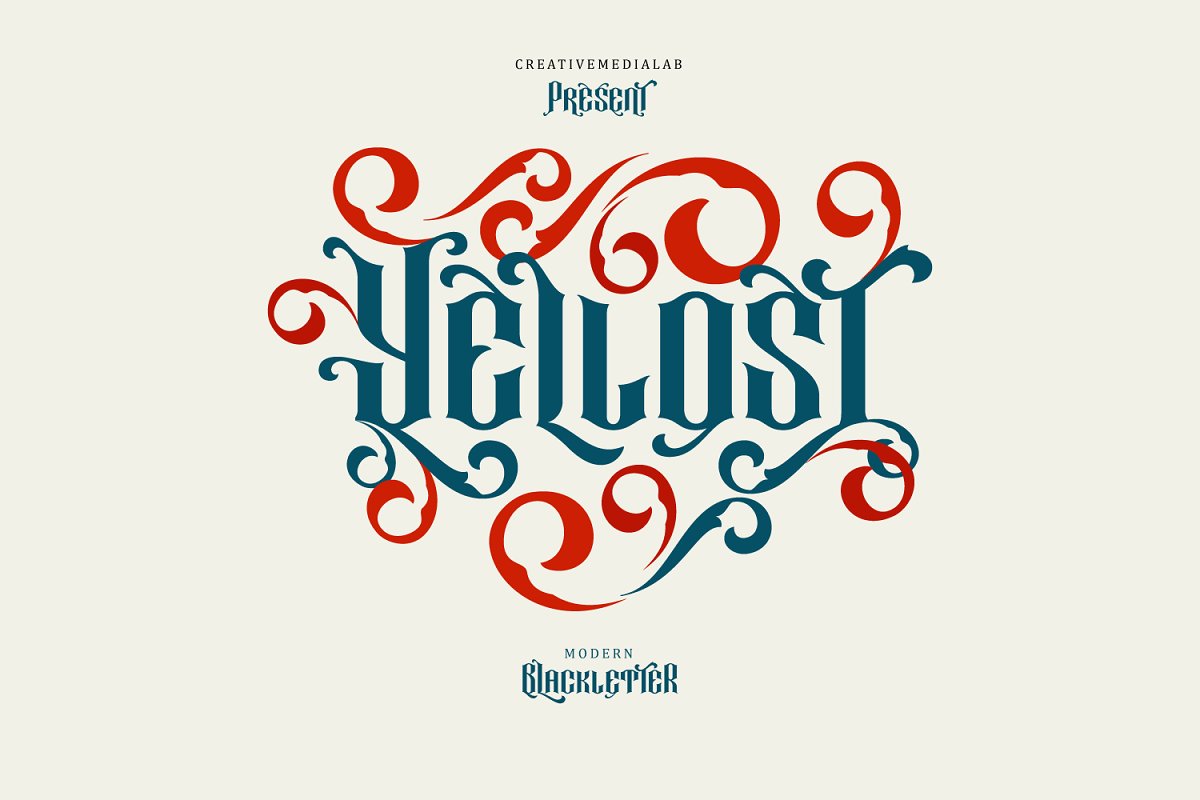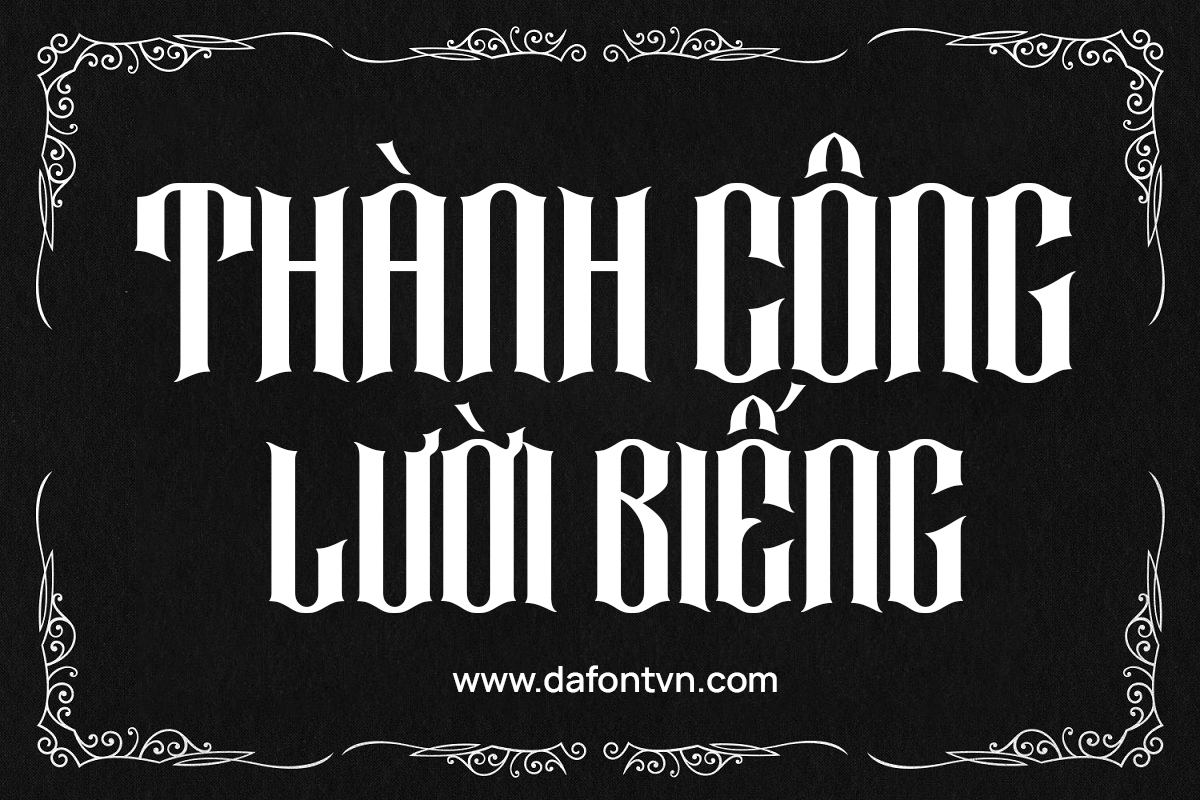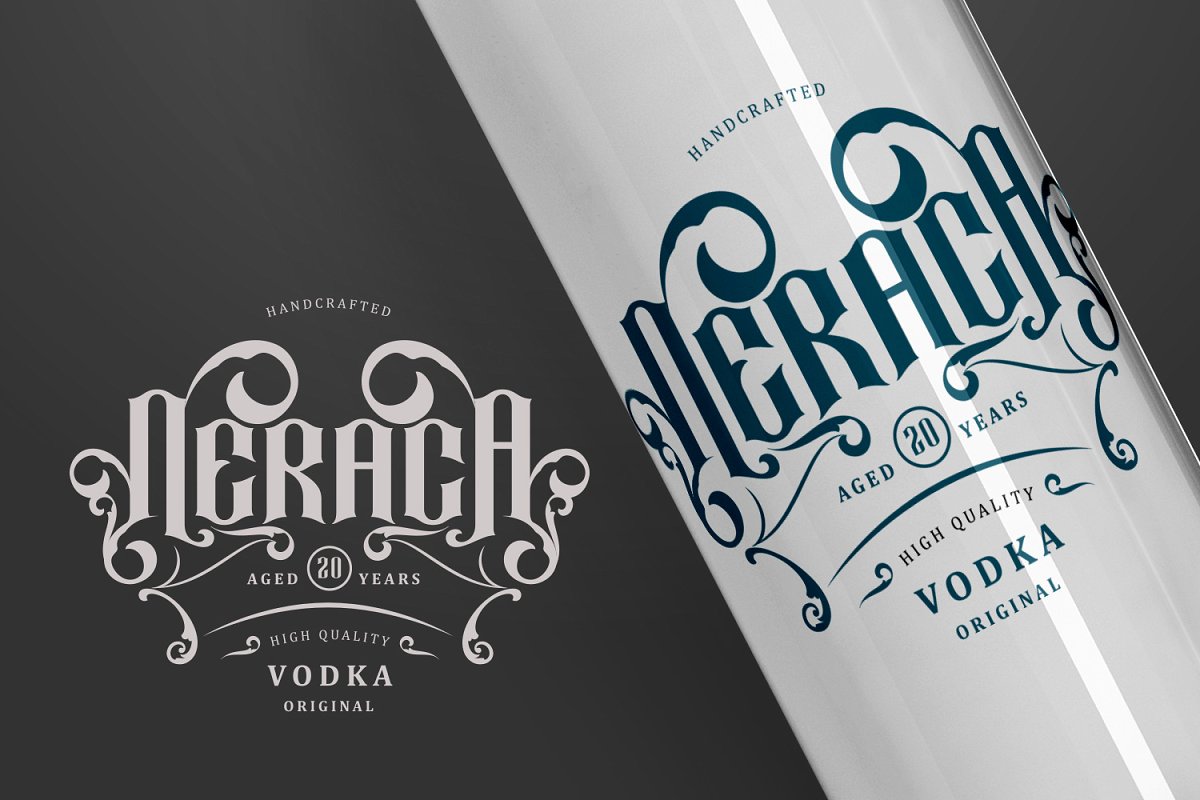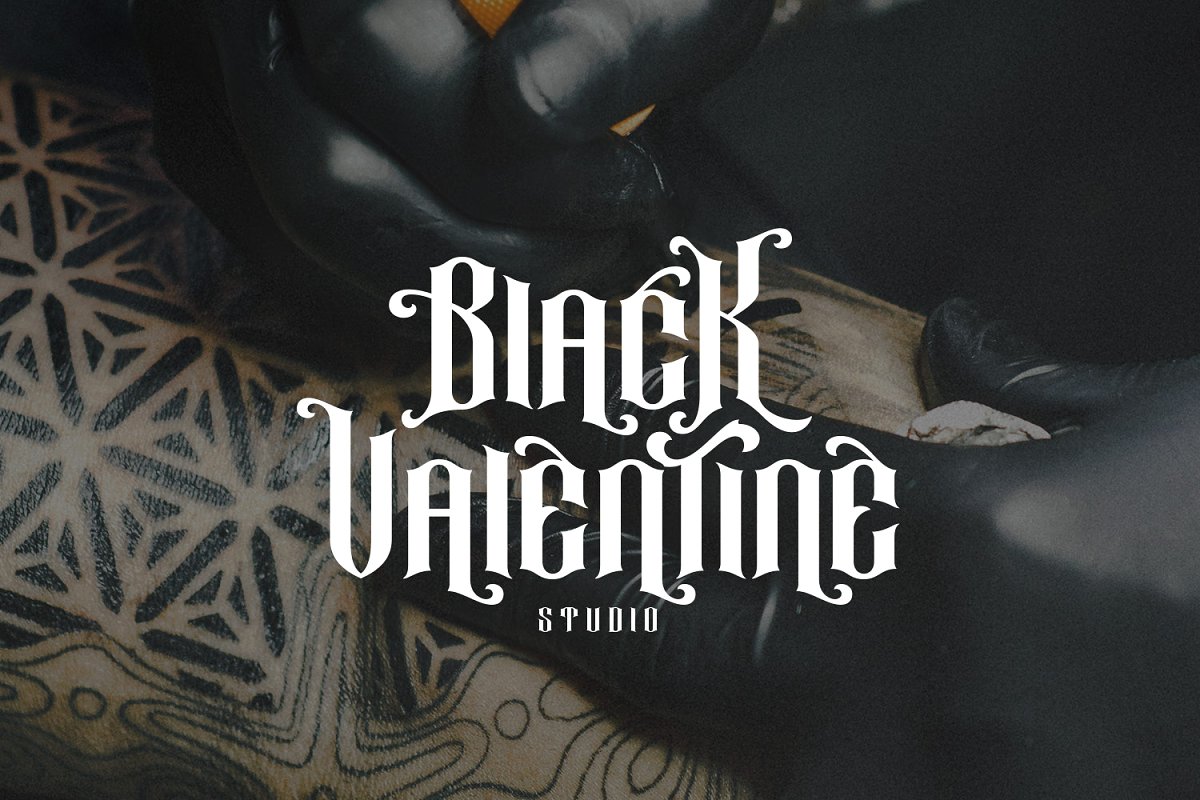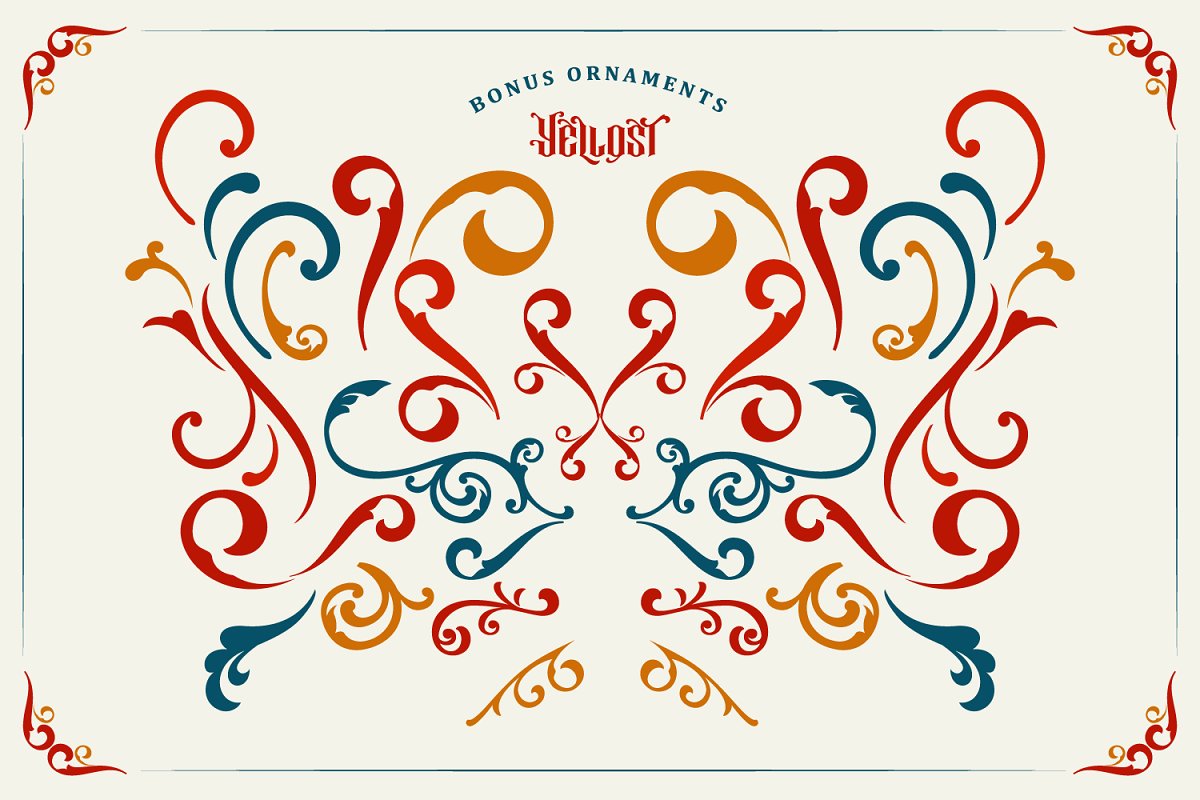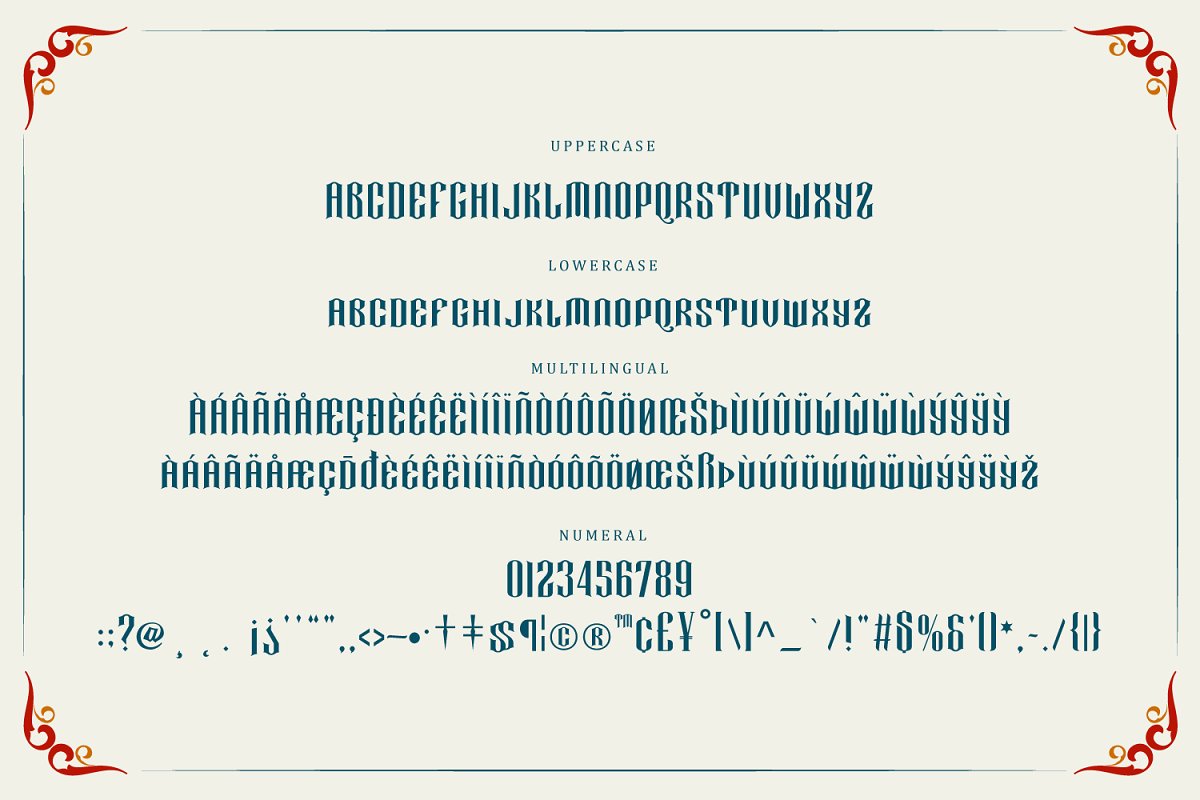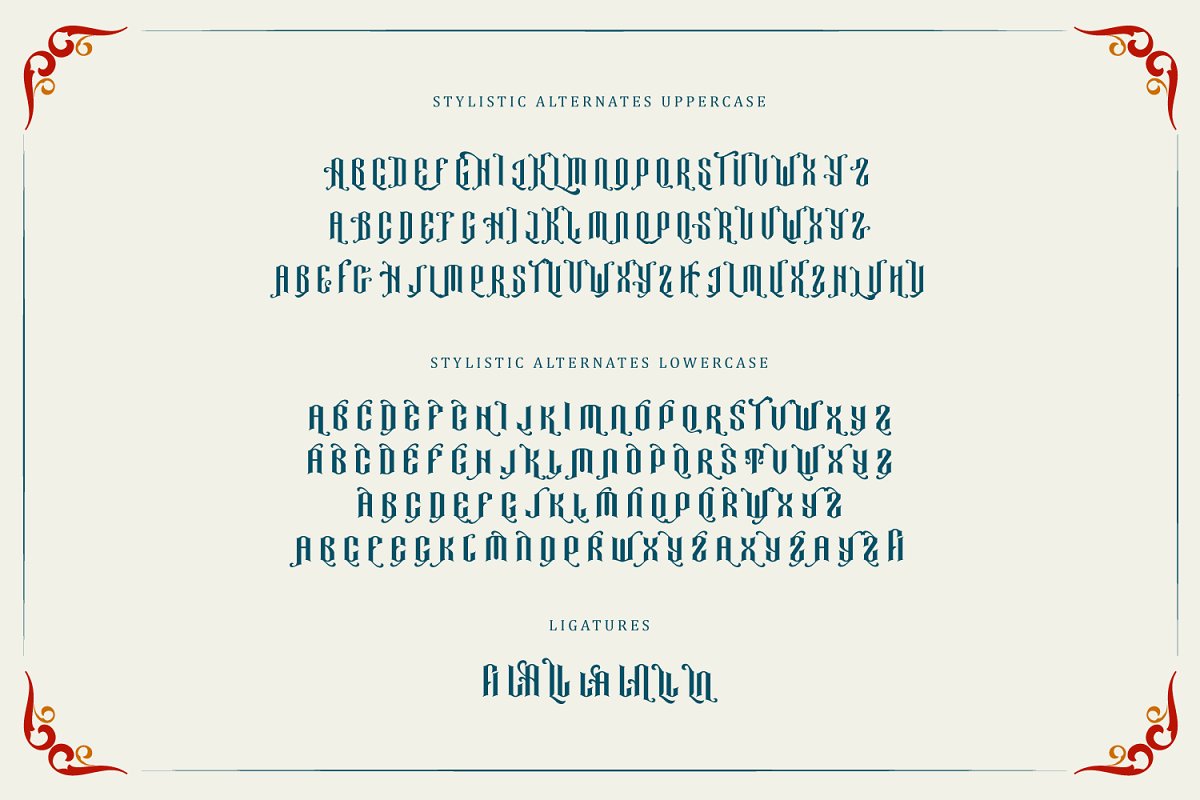
[Sans-Serif] Tải font Yellost Việt Hóa cực đẹp
Font chữ Yellost Việt Hóa, một font chữ độc đáo cho thiết kế của bạn để tạo nên cho các dự án tiếp theo của bạn. Phù hợp cho các thiết kế tattoo, gothic, nhãn hiệu quần áo, nhãn, bao bì và nhiều hơn nữa.